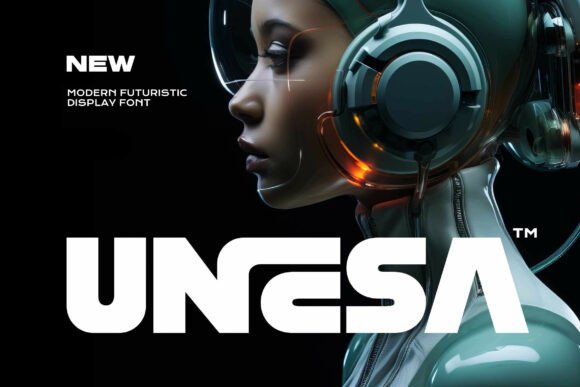
Unesa
Unesa Futuristic Font: A Revolução Tipográfica para Design Moderno
Se você está em busca de uma tipografia que una futurismo, sofisticação e versatilidade, a Unesa Futuristic Font chega como a solução perfeita. Ideal para projetos que vão de cartazes de cinema a design de camisetas esportivas, esta fonte traz um visual contemporâneo que destaca qualquer comunicação visual.
Por que escolher a Unesa?
- Design único: combina curvas suaves em minúsculas com cantos marcantes em maiúsculas, criando contraste visual que foge dos padrões tradicionais.
- Legibilidade total: funciona perfeitamente tanto em maiúsculas quanto em minúsculas, garantindo clareza em títulos, logotipos e textos curtos.
- Aplicação ampla: ideal para cabeçalhos, branding, capas de livros, convites de casamento, embalagens, mockups de produto, rótulos, editoriais e, claro, materiais esportivos como pôsteres e jerseys.
- Impacto visual: transmite vibração “strong‑bold”, perfeita para slogans, campanhas publicitárias e qualquer peça que precise de presença marcante.
Principais usos recomendados
- Cartazes de filmes sci‑fi e trailers
- Logotipos de marcas tech e street‑wear
- Convites de casamento e eventos corporativos
- Capa de livros e revistas de design
- Embalagens de produtos premium
- Design de jerseys, posters esportivos e slogans de equipes
- Campanhas de marketing digital e anúncios impressos
A Unesa Futuristic Font não é apenas mais uma tipografia; é uma ferramenta estratégica que eleva a identidade visual de qualquer projeto. Seu estilo ousado e, ao mesmo tempo, elegante, garante que sua marca se destaque em um mercado cada vez mais competitivo. Experimente Unesa hoje mesmo e descubra como transformar ideias criativas em experiências visuais inesquecíveis.